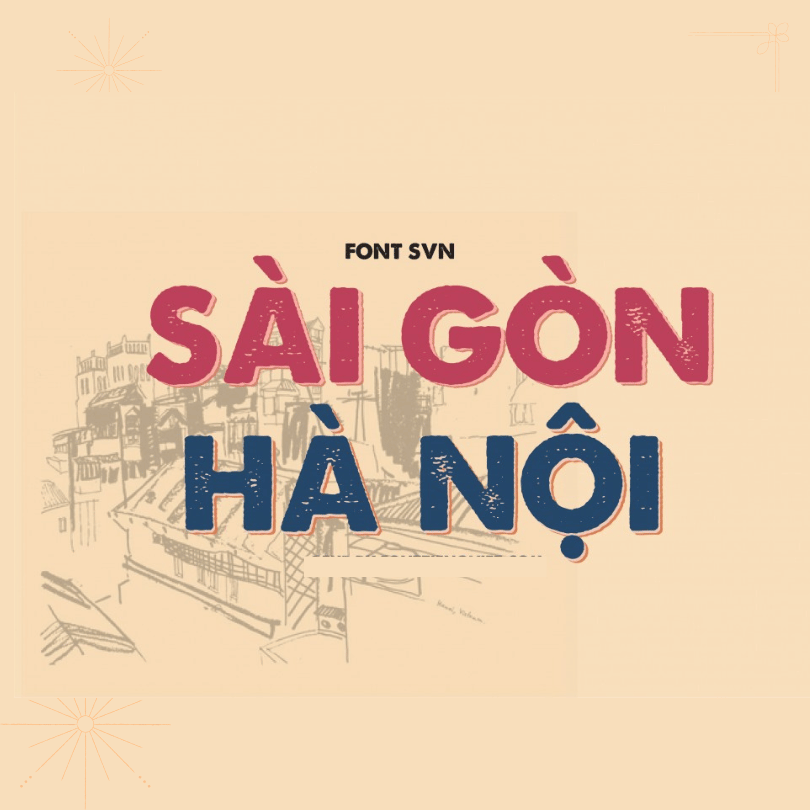
Việt hóa font SVN A Love Of Thunder
Việt Hóa Font SVN A Love Of Thunder
SVN A Love Of Thunder là một font chữ display (trang trí) với nét đậm, phong cách mạnh mẽ, thích hợp cho thiết kế poster, tiêu đề, hoặc các dự án cần sự nổi bật. Nếu font gốc chưa hỗ trợ tiếng Việt (thiếu dấu), bạn có thể thực hiện Việt hóa theo các cách sau:
1. Kiểm Tra Font Gốc
Trước tiên, hãy thử gõ tiếng Việt có dấu trong phần mềm như Photoshop, Illustrator hoặc Word:
• Nếu font hiển thị đúng dấu (ví dụ: “Xin chào” thành “Xin chào” thay vì “Xin chao”) → Font đã hỗ trợ tiếng Việt, không cần chỉnh sửa.
• Nếu thiếu dấu hoặc lỗi font → Cần Việt hóa.
2. Cách Việt Hóa SVN A Love Of Thunder
Cách 1: Sử Dụng Font Đã Việt Hóa Sẵn
Cách 2: Tự Việt Hóa Bằng Phần Mềm
Nếu bạn có kinh nghiệm chỉnh sửa font, có thể dùng:
Các bước cơ bản:
1. Mở font bằng phần mềm chỉnh sửa.
2. Thêm các ký tự tiếng Việt (ă, â, đ, ê, ô, ơ, ư, và các dấu sắc, huyền, hỏi, ngã, nặng).
3. Căn chỉnh vị trí dấu cho cân đối.
Cách 3: Dùng Font Tương Tự Hỗ Trợ Tiếng Việt
Nếu không tìm được bản Việt hóa, có thể thay thế bằng các font có phong cách tương tự:
3. Lưu Ý Khi Việt Hóa Font
• Tương thích Unicode: Đảm bảo font hỗ trợ chuẩn Unicode dựng sẵn để hiển thị đúng trên mọi phần mềm.
• Test kỹ: Sau khi chỉnh sửa, thử gõ nhiều từ có dấu để tránh lỗi.
Kết Luận